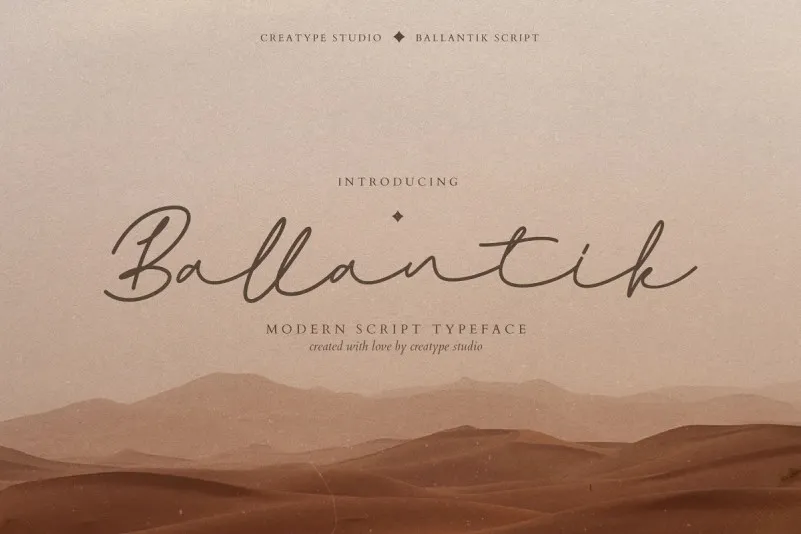
A fonte Ballantik é uma opção única para aqueles que buscam personalidade em seus projetos digitais. Ela se destaca por ser um tipo de script handwritten, com linhas fluidas e elegantes, criado com amor. Em cada caractere da fonte, você sente o encanto do estilo casual e fashionista, mas também a sofisticação e delicadeza que os profissionais adoram incorporar em seus designs. Perfect para ambientes de negócios modernos ou elementos únicos em projetos pessoais, esta fonte oferece um equilíbrio harmonioso entre elegância e casualidade. Seja você um designer gráfico proeminente ou alguém que busca incluir elementos diferentes em seu trabalho, Ballantik será uma escolha inteligente para suas necessidades de fontes criativas.